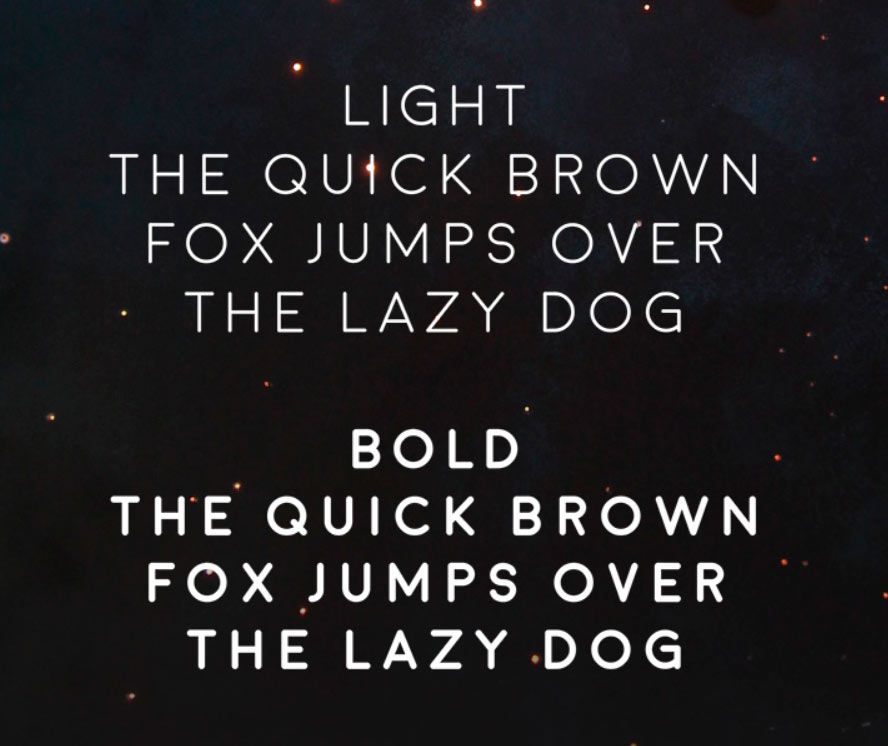
La tipografía elegida en nuestro especial Monday font de hoy se titula Moon. Creada por el diseñador e ilustrador Jack Harvatt. Un diseño simple, redondeado y sans serif.